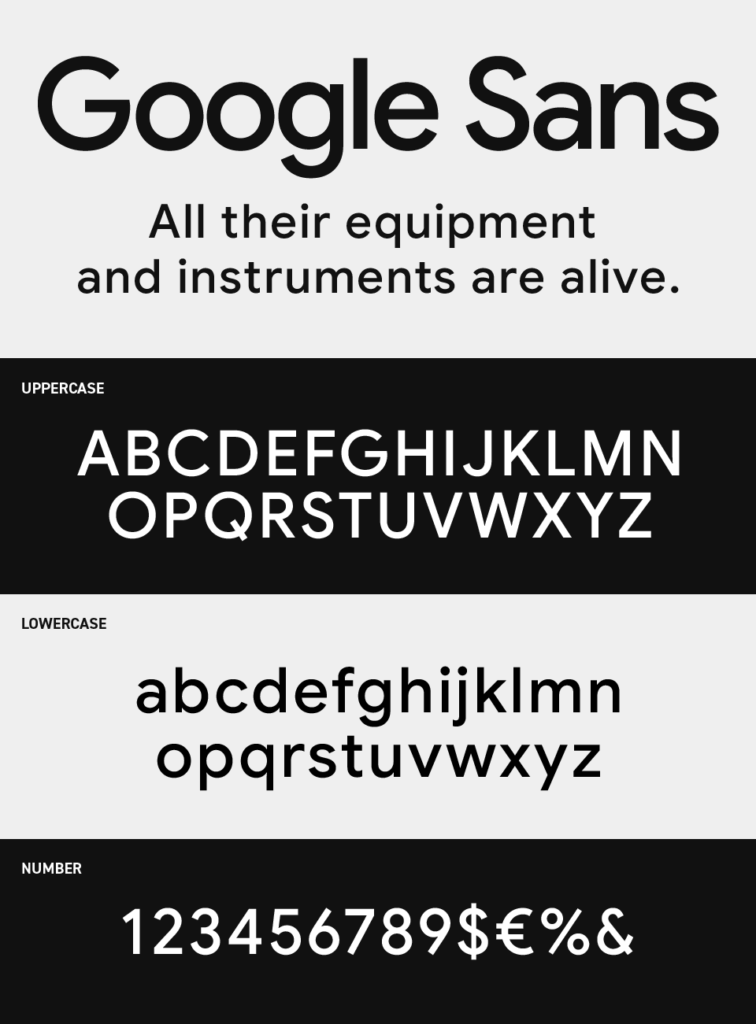
Google Sansフォントは、文字通りGoogleが自社ブランド向けとして制作したシンプルな骨格とやわらかな曲線が特徴の、モダンで親しみやすいサンセリフフォントです。
Googleのロゴやサービスにマッチするように、丸みを帯びた端部が冷たさを和らげ、テクノロジー系でありながら人間味のある印象で、文字間のバランスが整っているため、画面上での可読性が高く、アプリやWebサービスのインターフェースにマッチするように設計されています。
クセが少なく、それでいて個性もきちんと感じられるため、ブランドの信頼感を支えるベース書体として活躍するフォントです。